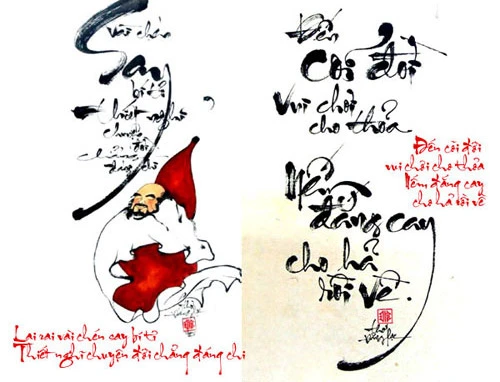
Tạo Dấu Ấn Tết Với Font Thư Pháp Việt Hóa
Bộ Font thư pháp 64 font chữ thư pháp tiếng Việt
Giới thiệu về bộ Font Thư Pháp
Trong không khí rộn ràng của dịp Tết Nguyên Đán, việc trang trí ngôi nhà và thể hiện tâm tư, tình cảm qua từng câu chữ trở thành một phần không thể thiếu trong văn hóa người Việt. Bộ font thư pháp Việt hóa không chỉ đơn thuần là những ký tự, mà là những tác phẩm nghệ thuật sống động có thể mang đến sức sống mới cho không gian của bạn.
Tại sao nên sử dụng font thư pháp?
Sử dụng bộ font thư pháp giúp bạn dễ dàng tạo ra những câu đối, thiệp chúc mừng hay các hình ảnh nghệ thuật lồng ghép chữ đẹp mắt. Với 64 font chữ khác nhau trong bộ font thư pháp, sự đa dạng trong mẫu chữ cho phép bạn thoải mái sáng tạo và thể hiện phong cách riêng của mình.
Những lợi ích của việc sử dụng font thư pháp
• Tạo cảm hứng sáng tạo: Mỗi mẫu chữ thư pháp đều mang một dáng vẻ riêng, giúp kích thích sự sáng tạo của bạn trong việc thiết kế các sản phẩm như thiệp mừng hay banner Tết.
• Giá trị nghệ thuật cao: Mỗi nét chữ trong font thư pháp đều được chăm chút tỉ mỉ, phản ánh tinh hoa của nghệ thuật viết chữ Việt Nam, mang đến cái nhìn thư thái và nghệ thuật cho mắt người nhìn.
Các loại font thư pháp trong bộ sưu tập
H2: Hai phân loại chính của font thư pháp
• Văn bản: Thư pháp văn bản có thể là một bài thơ hoặc một câu chúc mừng, rất thích hợp để viết trong các thiệp hoặc làm tài liệu.
• Tranh chữ (thư hoạ): Đây là loại hình chỉ sử dụng một từ hay một cụm từ ngắn và được trình bày trong một khung hình nhất định, rất phù hợp làm trang trí trong các dịp lễ hội.
H3: Các mẫu font thư pháp nổi bật
Bộ font thư pháp không chỉ đa dạng về kiểu dáng mà còn có nhiều mẫu chữ được yêu thích. Một số mẫu chữ tiêu biểu bao gồm:
• Lộc
• Phát
• Tài
Mỗi mẫu chữ mang một ý nghĩa riêng biệt và có thể dùng để chúc phúc, mang lại may mắn trong năm mới.
Tạo dòng chữ nghệ thuật với font thư pháp
H2: Cách sáng tạo hình nền Tết độc đáo
Sử dụng font thư pháp để tạo hình nền Tết là một ý tưởng thú vị giúp bạn biểu đạt cá tính và phong cách riêng. Dưới đây là một số bước để bạn có thể thực hiện:
• Chọn mẫu chữ: Duyệt qua bộ font thư pháp và chọn một hoặc vài mẫu mà bạn yêu thích nhất.
• Bố cục hợp lý: Đặt các dòng chữ một cách hài hòa và hợp lý, có thể:
- Sử dụng câu chúc Tết truyền thống. - Kết hợp với hình ảnh nền hoặc họa tiết trang trí.
• Điều chỉnh màu sắc: Chọn màu sắc cho chữ và nền sao cho tương phản, tạo sự nổi bật.
Nơi có thể sử dụng font thư pháp
H2: Font thư pháp trong đời sống hàng ngày
Font thư pháp không chỉ đơn giản là sử dụng trong các tài liệu nhưng nó còn có thể được áp dụng trong nhiều lĩnh vực khác nhau, như:
• Thiệp chúc mừng: Trang trí các thiệp chúc Tết, lễ cưới hay các dịp lễ hội.
• Thiết kế poster: Tạo ra các poster nghệ thuật cho sự kiện văn hóa.
• Quảng cáo và tiếp thị: Font thư pháp có thể được sử dụng trong quảng cáo sản phẩm nhằm tạo sự thu hút và khác biệt.